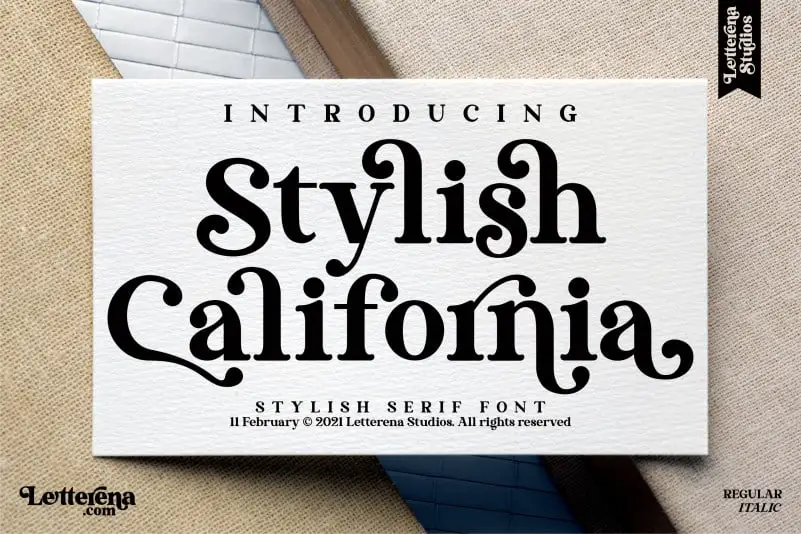
Aqui está uma descrição em português para a página de download da font ‘Stylish California Font’, que é adequada ao estilo elegante sugerido pela descrição original: A ‘Stylish California Font’ é uma font séria, ou serifada, ideal para projetos de alto nível. Seu design detalhado e sofisticado se destaca em estilos como logomarcas, embalagens de produtos, cartões de visita, revistas e livros. Proporcionando um toque elegante e sofisticado que complementa perfeitamente qualquer projeto requintado ou decorativo, esta font é perfeita para personalizar uma gama completa de materiais, incluindo: embalagens de produto, tags, selos, capas de livros e até mesmo a própria etiqueta. Ela se ajusta perfeitamente em cartões de convite, cartazes, revistas, adesivos ou até mesmo como um toque final nos vídeos ou fotografias que você deseja destacar com elegância. A ‘Stylish California Font’ é uma escolha ótima para designers buscando dar um toque sofisticado a seus trabalhos. É perfeita para aqueles projetos onde uma fonte de estilo clássico e luxuoso irá ressaltar o valor e a qualidade do design. Além disso, a fonte é também perfeitamente adaptável aos materiais impressos e digitais, oferecendo um alto nível de precisão e controle para as designers que desejam maximizar o impacto visual em suas criações.